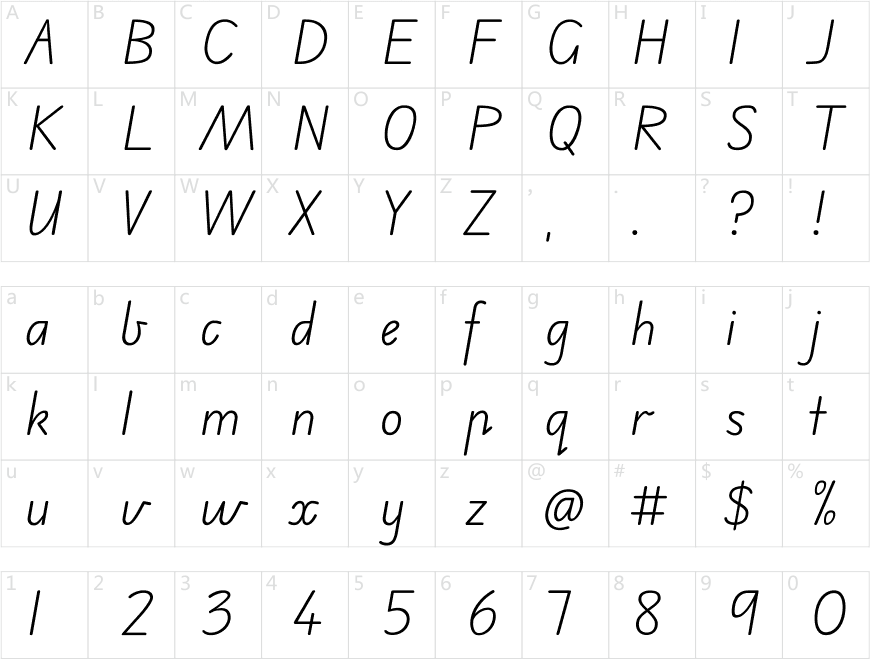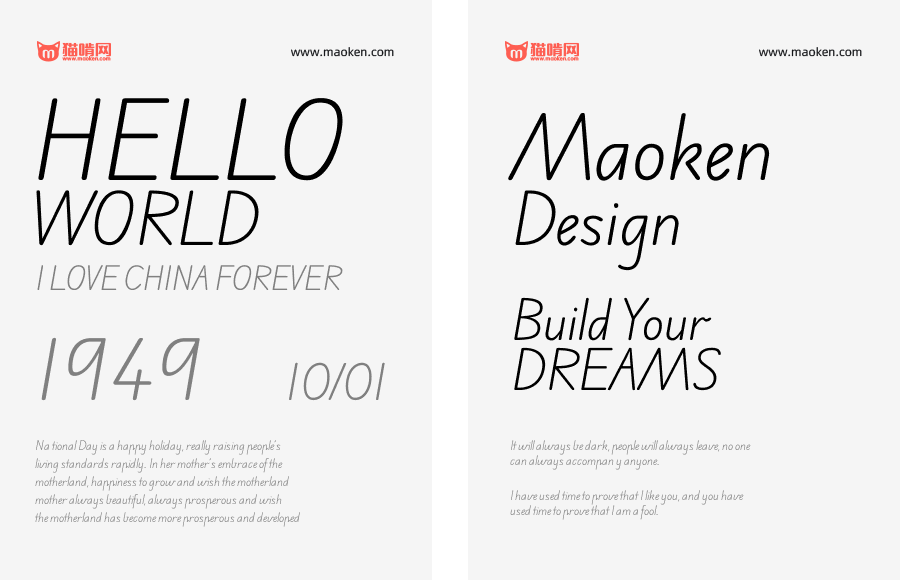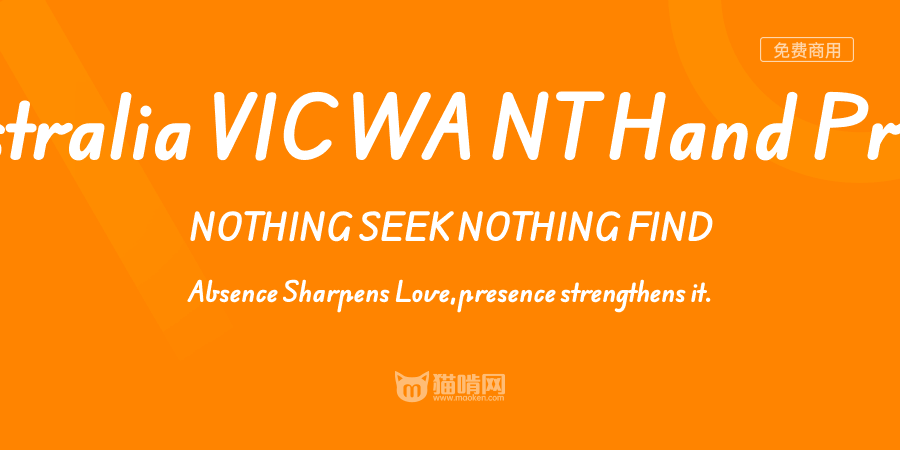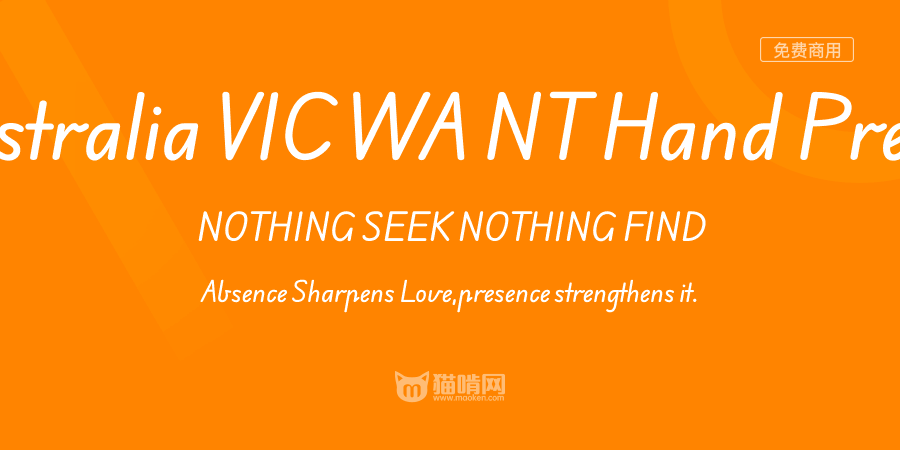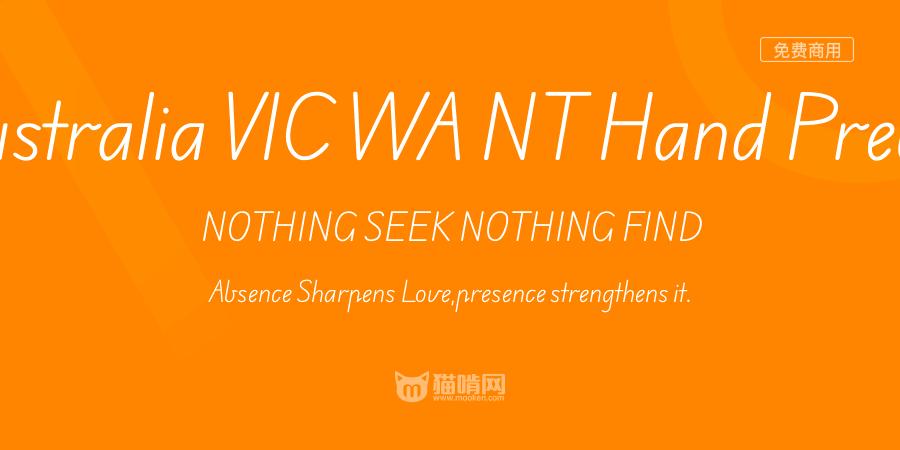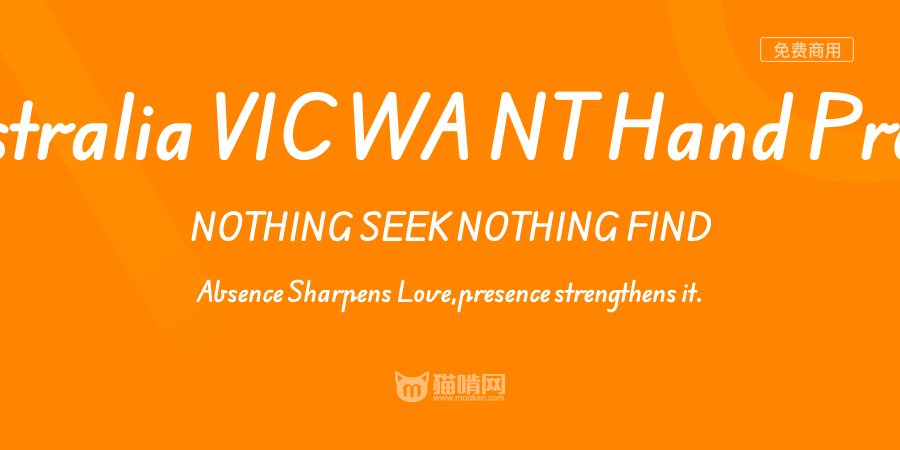
Edu Australia VIC WA NT Hand Precursive
AU手写教育字体是一套英文OpenType可变字体,专为满足澳大利亚教育标准而设计。这些字体的粗细、宽度和光学尺寸都经过精心调整,不仅适合澳大利亚的课堂环境,在家庭环境中阅读和使用也同样舒适。
该字体展现了维多利亚州、西澳大利亚州和北领地的书写风格。